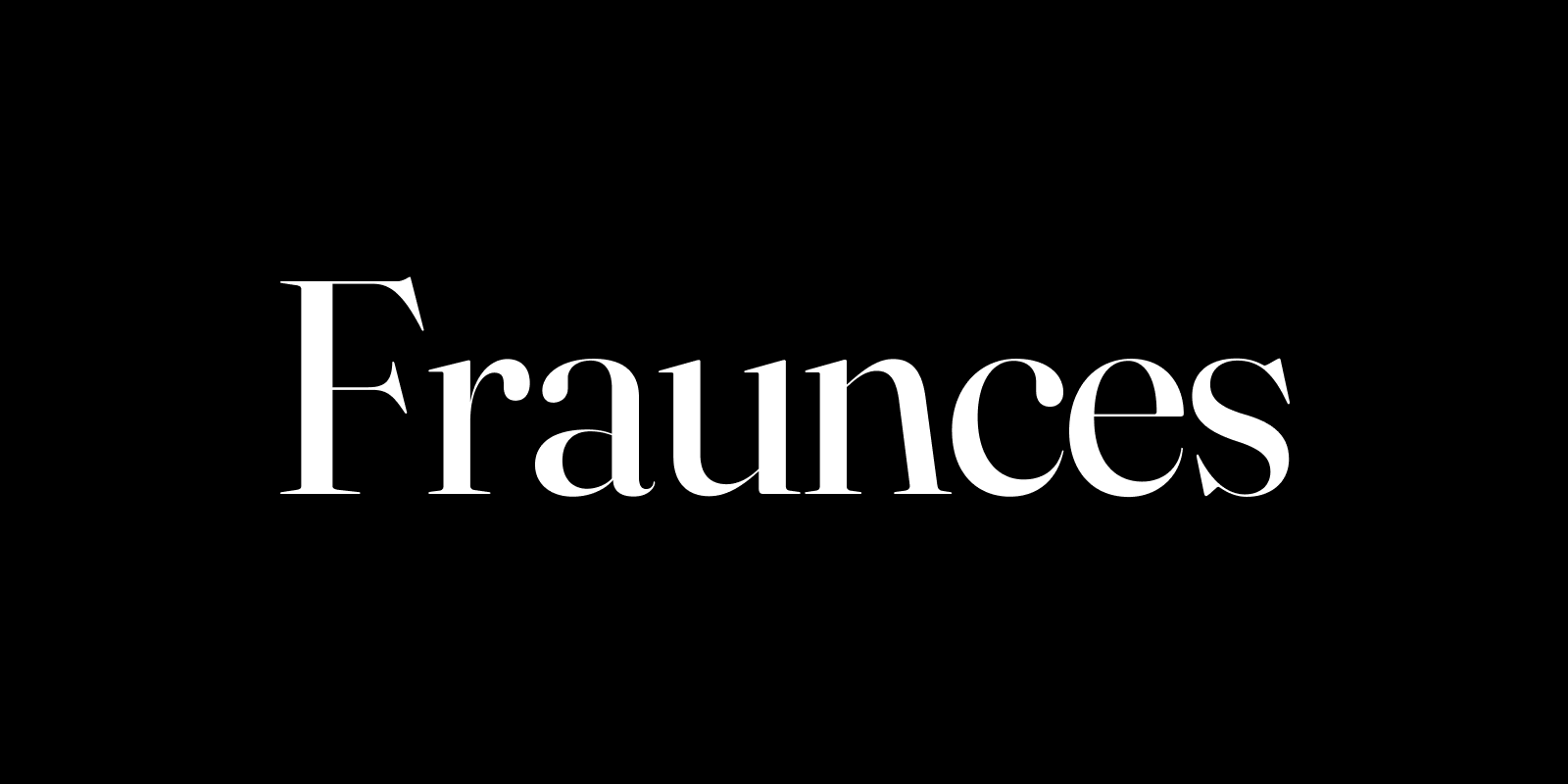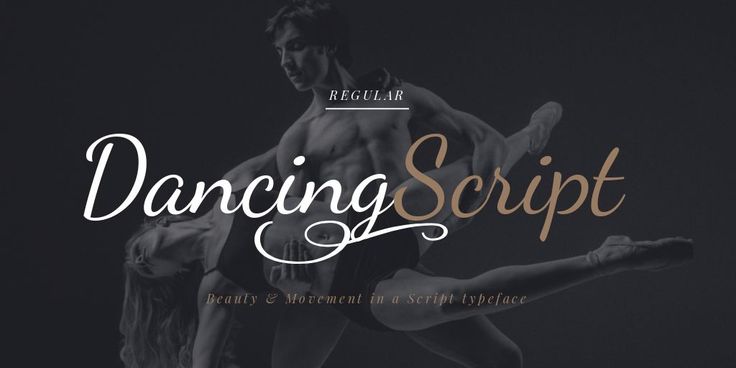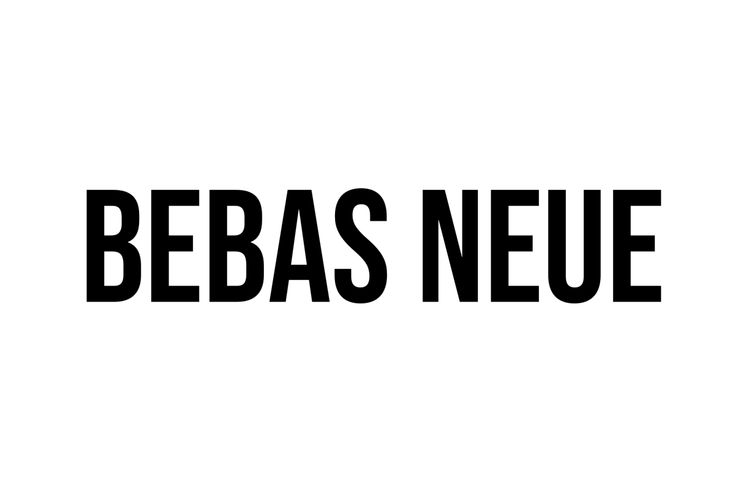
Bisnis cafe telah mengalami pertumbuhan cukup sehingga banyak orang tertarik membangun brand untuk bisnis cafe dengan menarik. Desain untuk logo cafe biasanya memiliki tampilan elegan, sederhana dan mewah, brand cafe akan tampak elegan dnegan jenis font seperti serif, sans serif dan script. . Kesederhanaan elemen visual seperti font dan ikon logo adalah rahasia kesuksesan membangun brand cafe.
Untuk membangun brand cafe, tentukan lebih dulu tema atau gaya desain yang ingin diciptakan. Umumnya brand cafe akan memiliki tampilan logo yang minimalis, elegan dan bersih. Terkadang juga menggunakan gaya vintage atau klasik karena cocok dengan citra brand cafe yang sering estetik.
TIPS MENGGUNAKAN FONT UNTUK BRAND CAFE
Dalam desain logo untuk brand cafe penggunaan elemen visual seperti cukup khas, seiringnya sederhana, elegan dan vintage. Untuk memilih font logo cafe yang menarik dan relevan, pertimbangkan beberapa hal ini:
Gunakan Font yang Sederhana dan Elegan
Untuk digunakan sebagai identitas merek, penting untuk memilih jenis font yang sederhana dan elegan agar terbaca dengan baik. Penggunaan font sederhana akan membantu brand cafe tampil elegan dan minimalis. Font tebal dan rumit jarang digunakan pada brand cafe karena kurang efektif.
Kesederhanaan dan keterbacaan font harus diutamakan karena tidak hanya digunakan untuk logo cafe. Cafe akan menggunakan jenis font logo sebagai identitas merek, sehingga digunakan untuk kebutuhan lain seperti font teks pada cup coffee, desain menu hingga stiker. Untuk pastikan memilih font dengan keterbacaan yang baik agar mudah dibaca.
Kombinasikan Dua Font yang Estetik dan Kontras
Pada desain logo bisnis cafe terkadang membutuhkan dua jenis font, untuk nama cafe dan tagline. Kombinasikan dua font yang kontras gaya dan ukurannya tetapi masih mudah dibaca. Misalnya kombinasi sans serif dengan font script yang elegan akan terlihat kontras dan menarik.
Meski kontras jenis font yang dikombinasikan harus tampil harmonis dan merepresentasikan brand cafe dengan baik. Umumnya kombinasi yang cocok memiliki jenis font yang tampil elegan dan mudah dibaca. Jika cafe memiliki gaya vintage gunakan kombinasi serif klasik dengan script.
Variasikan Ukuran Nama Merek dengan Tagline
Agar desain logo brand cafe tampil menarik, pastikan antara teks judul nama cafe dan tagline memiliki font dan ukuran berbeda. Tidak hanya untuk menciptakan kontras dan hirarki visual, tetapi juga efektif meningkatkan keterbacaan. Perbedaan jenis font saja tidak cukup tetapi juga harus menggunakan ukuran yang berbeda.
Font nama cafe bisa berukuran lebih besar, dan tagline bisa menggunakan ukuran yang lebih kecil. Pastikan variasi ukuran teks menciptakan skala yang harmonis dan tidak terlalu aneh. Hindari menggunakan ukuran yang sama antara nama merek dan tagline meski sudah menggunakan jenis font berbeda karena akan kurang jelas perbedaannya.
Tambahkan Dekorasi yang Relevan
Terkadang dalam desain logo brand cafe, penggunaan font yang unik saja kurang cukup menarik. Untuk membuat font tampil lebih estetik terkadang dilakukan modifikasi yang menarik. Penggunaan tambahan dekorasi dau atau ornamen kerap ditambahkan pada jenis font elegan seperti script atau serif.
Dekorasi font akan lebih menarik dengan ditambahkan juga garis-garis melengkung atau tambahan panjang huruf. Ornamen melengkung sederhana membuat teks dalam desain logo cafe lebih unik dan elegan. Pastikan dekorasi untuk jenis font sesuai dengan tema desain dan karakter brand agar efektif.
JENIS FONT YANG UMUM UNTUK DESAIN BRAND CAFE
Gaya font yang digunakan dalam desain brand cafe seringkali menggunakan gaya huruf sederhana dan elegan. Beberapa jenis font yang umum digunakan dalam brand logo cafe, seperti:
- Serif Modern dan Klasik
- Sans Serif Regular
- Script Tipis yang Elegan
- Handwritten Sederhana dan Mudah Dibaca
Biasanya logo cafe jarang ada yang menggunakan jenis font yang kaku atau tajam, tetapi menggunakan jenis font dengan ujung lancip dan melengkung. Pemilihan jenis font dan kombinasi yang cocok akan efektif mencerminkan brand cafe.
5 FONT ELEGAN UNTUK BRAND CAFE
Saat memilih gaya font yang cocok untuk branding bisnis cafe, pertimbangkan tema cafe, penggunaan font hingga kesan yang ingin diciptakan. Beberapa brand cafe mungkin ingin terlihat modern, klasik atau elegan, yang mana membutuhkan jenis font berbeda. Berikut beberapa rekomendasi font untuk brand cafe yang estetik dan elegan:
Gracela
Untuk digunakan dalam desain bisnis cafe gaya font yang elegan seperti font Gracela ini akan menciptakan desain logo yang elegan. Jenis font ini termasuk dalam jenis sans serif elegan, oleh karena itu font ini memiliki tampilan huruf yang bersih, sudut tajam dan elegan. Gaya huruf yang elegan membuat jenis font ini akan relevan dengan citra bisnis kafe yang estetik.
Untuk menciptakan desain branding cafe yang relevan, pemilihan gaya font harus sesuai dengan pesan dan karakter merek. Bisnis cafe seringkali menggunakan gaya desain minimalis, sederhana dan elegan yang mana mempengaruhi jenis font. Beberapa font yang direkomendasikan untuk digunakan dalam bisnis cafe bisa menggunakan font serif, script, handwritten, dan san serif yang tampil elegan dan tipis.